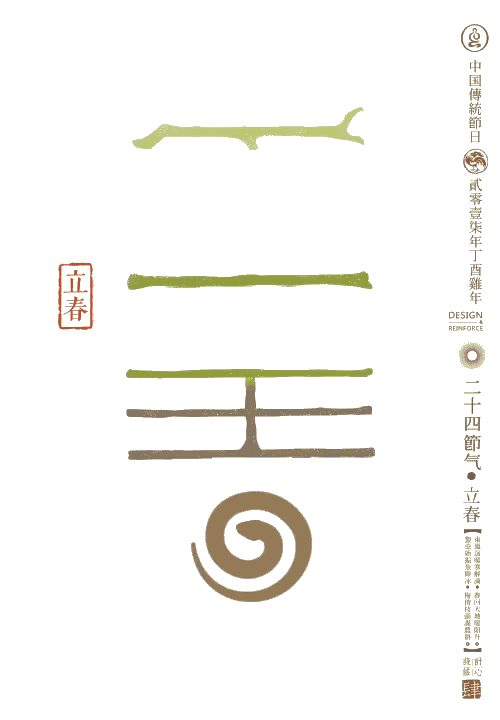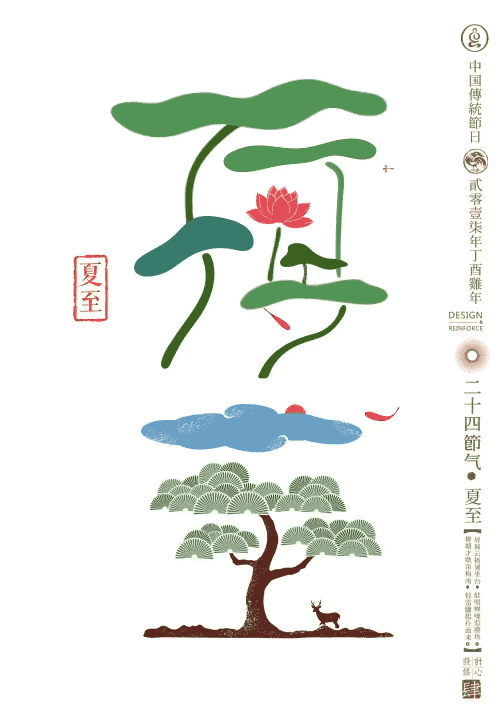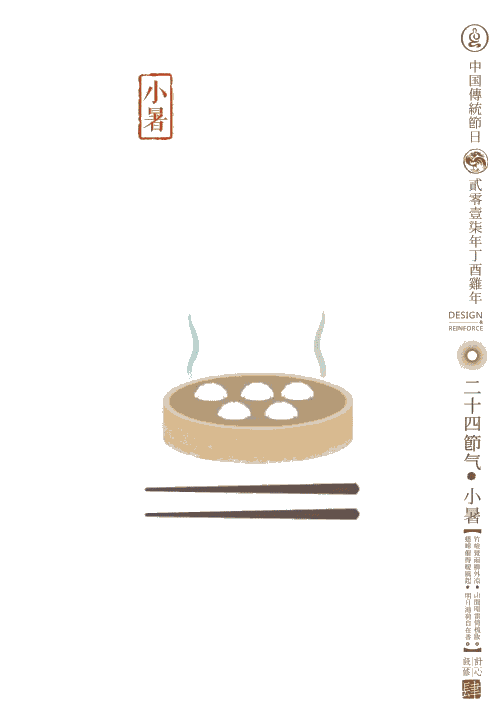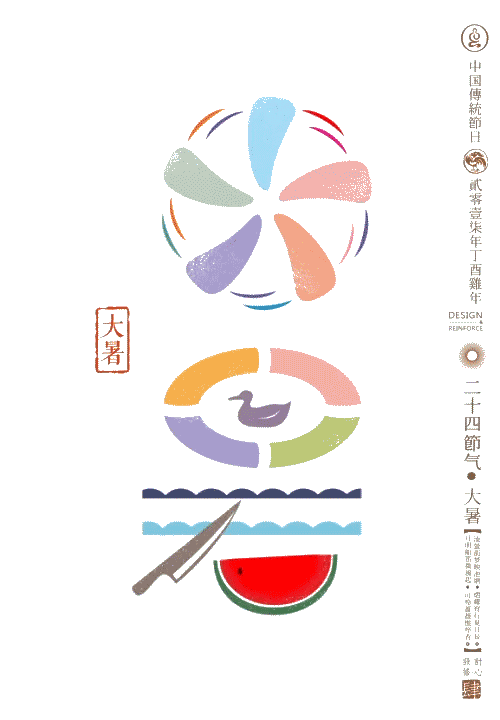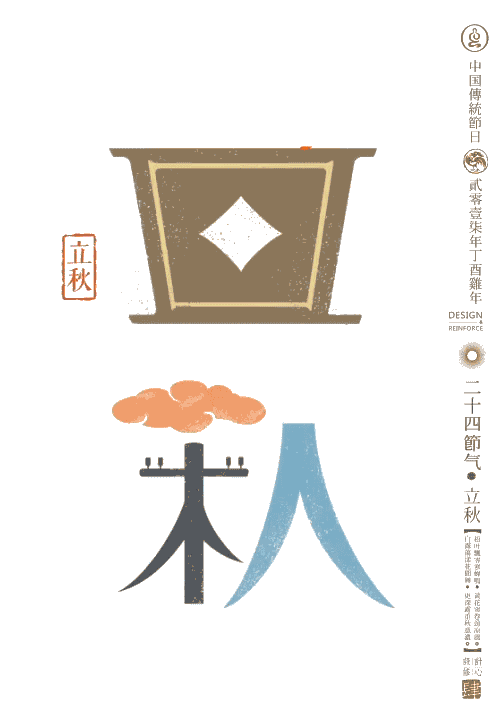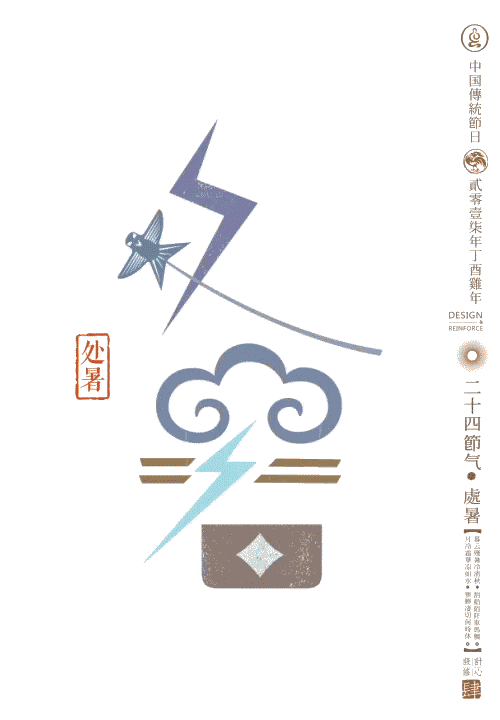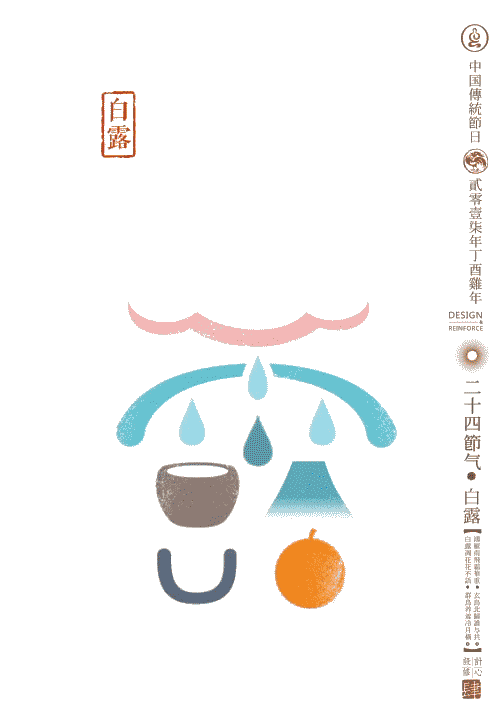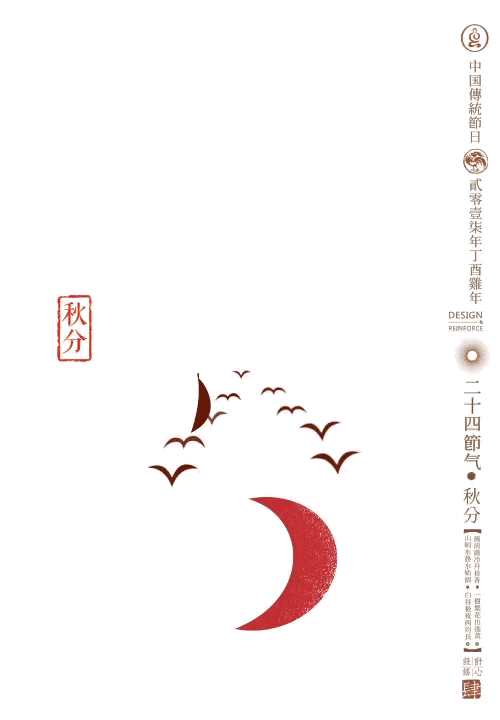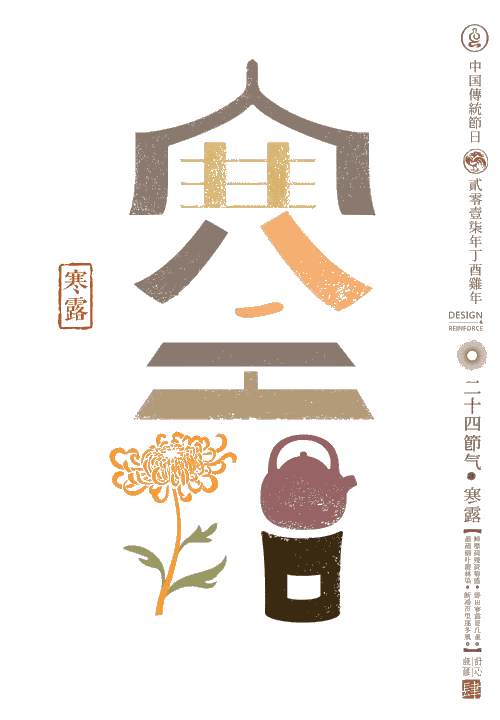
魅力中国——24节气字体设计,全世界都震惊了!
一位来自贵阳的设计师石昌鸿创造了一套24节气的动图,清新的中国风加上小诗,惟妙惟肖、生动有趣,一下子就道出了传统节气的寓意,连小孩子都能看懂,并成功申遗,惊艳了全世界!
作品名称:魅力中国——24节气字体设计
主创设计:石昌鸿
动画:任小波 王忠 李志念
文案:史万青 冯小鱼 李明灯
艺术指导:郭超
【立春】
万物复苏,耕耘播种
啼莺舞燕,绿芽萌动
蛰虫始振阳气生
惠嵩春江晚景
苏轼
竹外桃花三两枝,春江水暖鸭先知。
蒌蒿满地芦芽短,正是河豚欲上时。
立春:立是开始的意思,立春就是春季的开始。
【雨水】
潇潇细雨天渐暖
雨水纷纷送肥忙
春夜喜雨
杜甫
好雨知时节,当春乃发生。
随风潜入夜,润物细无声。
雨水:降雨开始,雨量渐增。
【惊蛰】
春雷响,万物长
一声霹雳醒蛇虫
天气回暖雨水降
观田家
韦应物
微雨众卉新,一雷惊蛰始。
田家几日闲,耕种从此起。
惊蛰:蛰是藏的意思。惊蛰是指春雷乍动,惊醒了蛰伏在土中冬眠的动物。
【春分】
庭院深深深几许,杨柳依依拂心田
白天黑夜两均分,春意融融燕子归
春分
苏醒
春分雨脚落声微,柳岸斜风带客归。
时令北方偏向晚,可知早有绿腰肥。
春分:分是平分的意思,春分表示昼夜平分。
【清明】
细雨纷纷,春茶正香
扫墓祭祖,春游踏青
植树造林,杨柳长青
清明
唐 杜牧
清明时节雨纷纷,路上行人欲断魂。
借问酒家何处有?牧童遥指杏花村。
清明:天气晴朗,草木繁茂。
【谷雨】
雨生百谷,谷雨断霜
祈福消灾祭仓颉
七言诗
郑板桥
不风不雨正晴和,翠竹亭亭好节柯。
最爱晚凉佳客至,一壶新茗泡松萝。
几枝新叶萧萧竹,数笔横皴淡淡山。
正好清明连谷雨,一杯香茗坐其间。
谷雨:雨生百谷。雨量充足而及时,谷类作物能茁壮成长。
【立夏】
蝼蝈鸣,蚯蚓出
田埂野菜日日长
立夏
宋 赵友直
四时天气促相催,一夜薰风带暑来。
陇亩日长蒸翠麦,园林雨过熟黄梅。
莺啼春去愁千缕,蝶恋花残恨几回。
睡起南窗情思倦,闲看槐荫满亭台。
立夏:夏季的开始。
【小满】
鸟衔樱红笑插秧
垄头麦穗始灌浆
归田园四时乐春夏二首(其二)
欧阳修
野棠梨密啼晚莺,海石榴红啭山鸟。
田家此乐知者谁?我独知之归不早。
小满:麦类等夏熟作物籽粒开始饱满。
芒种
芒种时节样样忙
鸟儿鱼儿把歌唱
梅雨潇潇涨池塘
时雨
陆游
时雨及芒种,四野皆插秧。
家家麦饭美,处处菱歌长。
芒种:麦类等有芒作物成熟。
【夏至】
鹿角脱落,蝉鸣不休
江南梅雨连绵,池荷锦鲤畅游
竹枝词
刘禹锡
杨柳青青江水准,闻郎江上唱歌声。
东边日出西边雨,道是无晴还有晴。
夏至:炎热的夏天来临。
【小暑】
炎热温风至,雪糕解暑凉
行人外出皆遮伞,开胃靠饺子解馋
幸有心期当小暑
韩翃
朝辞芳草万岁街,暮宿春山一泉坞。
青青树色傍行衣,乳燕流莺相间飞。
小暑:暑是炎热的意思。小暑就是气候开始炎热。
【大暑】
高温酷热三伏天,懒摇风扇纳清凉
池塘嬉戏避炎热,西瓜味美正甘甜
夏日闲放
白居易
时暑不出门,亦无宾客至。
静室深下帘,小庭新扫地。
褰裳复岸帻,闲傲得自恣。
朝景枕簟清,乘凉一觉睡。
午餐何所有,鱼肉一两味。
夏服亦无多,蕉纱三五事。
资身既给足,长物徒烦费。
若比箪瓢人,吾今太富贵。
大署:一年中最热的时候。
【立秋】
暑去凉来,落叶知秋
寒蝉凄切禾谷成熟
立秋日
令狐楚云
平日本多恨,新秋偏易悲。
燕词如惜别,柳意已呈衰。
事国终无补,还家未有期。
心中旧气味,苦校去年时。
立秋:秋季的开始。
【处暑】
秋雨寒凉,禾谷满仓
秋高气爽,人间雷降
长江二首
苏泂
处暑无三日,新凉直万金。
白头更世事,青草印禅心。
放鹤婆娑舞,听蛩断续吟。
极知仁者寿,未必海之深。
处暑:处是终止、躲藏的意思。处暑是表示炎热的暑天结束。
【白露】
凉风至,白露降
寒蝉鸣,鸿雁归
正值柑橘肥美时
八月十九日试院梦冲卿
王安石
空庭得秋长漫漫,寒露入暮愁衣单。
喧喧人语已成市,白日未到扶桑间。
永怀所好却成梦,玉色彷佛开心颜。
逆知后应不复隔,谈笑明月相与闲。
白露:天气转凉,露凝而白。
【秋分】
秋分祭月,昼夜均长
水涸田龟裂,桂子飘香
夜喜贺兰山见访
贾岛
漏钟仍夜浅,时节欲秋分。
泉聒栖松鹤,风除翳月云。
踏苔行引兴,枕石卧论文。
即此寻常静,来多只是君。
秋分:昼夜平分。
【寒露】
袅袅凉风,饮菊煮酒
夜色凉如水,草木梧桐黄
池上
白居易
嫋嫋凉风动,凄凄寒露零。
兰衰花始白,荷破叶犹青。
独立栖沙鹤,双飞照水萤。
若为寥落境,仍值酒初醒。
寒露:露水以寒,将要结冰。
【霜降】
天气渐冷,露水凝霜
红柿甘甜绵软,枫叶如火似锦
蒹葭
诗经
蒹葭苍苍,白露为霜。所谓伊人,在水一方。
溯洄从之,道阻且长。溯游从之,宛在水中央。
蒹葭萋萋,白露未晞。所谓伊人,在水之湄。
溯洄从之,道阻且跻。溯游从之,宛在水中坻。
蒹葭采采,白露未已。所谓伊人,在水之涘。
溯洄从之,道阻且右。溯游从之,宛在水中沚。
霜降:天气渐冷,开始有霜。
【立冬】
江水初凝,冬雷震震
万物收藏,归避寒冷
立冬
李白
冻笔新诗懒写,寒炉美酒时温。
醉看墨花月白,恍疑雪满前村。
立冬:冬季的开始。
【小雪】
太行初飘雪,千山鸟飞绝
农户忙贮菜,蓄以御冬寒
白雪歌武判官归
岑参
北风卷地白草折,胡天八月即飞雪。
忽如一夜春风来,千树万树梨花开。
小雪:开始下雪。
【大雪】
千里冰封,万里雪飘
天寒地冻,腊肉熏香
江雪
柳宗元
千山鸟飞绝,万径人踪灭。
孤舟蓑笠翁,独钓寒江雪。
大雪:降雪量增多,地面可能积雪。
【冬至】
暴雪低温,万旅不商
南火锅北饺子,腊梅竞开放
小至
杜甫
天时人事日相催,冬至阳生春又来。
刺绣五纹添弱线,吹葭六琯动浮灰。
岸容待腊将舒柳,山意冲寒欲放梅。
云物不殊乡国异,教儿且覆掌中杯。
冬至:寒冷的冬天来临。
【小寒】
小寒大寒,冷成冰团
幽阖大雪红炉暖
小寒食舟中作
杜甫
佳辰强饭食犹寒,隐几萧条带鹖冠。
春水船如天上坐,老年花似雾中看。
娟娟戏蝶过闲幔,片片轻鸥下急湍。
云白山青万馀里,愁看直北是长安。
小寒:气候开始寒冷。
【大寒】
雨雪纷飞,腊八飘香
炮竹声声,年味浓浓
大寒
陆游
大寒雪未消,闭户不能出,
可怜切云冠,局此容膝室。
吾车适已悬,吾驭久罢叱,
拂麈取一编,相对辄终日。
亡羊戒多岐,学道当致一,
信能宗阙里,百氏端可黜。
为山傥勿休,会见高崒嵂,
颓龄虽已迫,孺子有美质。
大寒:一年中最冷的时候。
谈及创作初衷,石昌鸿希望能通过一种通俗易懂、老少咸宜的表现手法,让民众了解二十四节气,农村生活的零距离体验也在他创作过程中发挥了“功臣”的作用,图中冬眠苏醒后的蛇、往南飞的大雁、寒蝉等都描绘得活灵活现、惟妙惟肖。
“不求做得高深莫测,只求能兼顾美感识别的同时,一定要小孩子都看得懂,觉得生动有趣,一看就代表节气的文化符号。”石昌鸿在采访中说到,只有人们有兴趣才会深入地去认识和了解,并将其发扬光大。